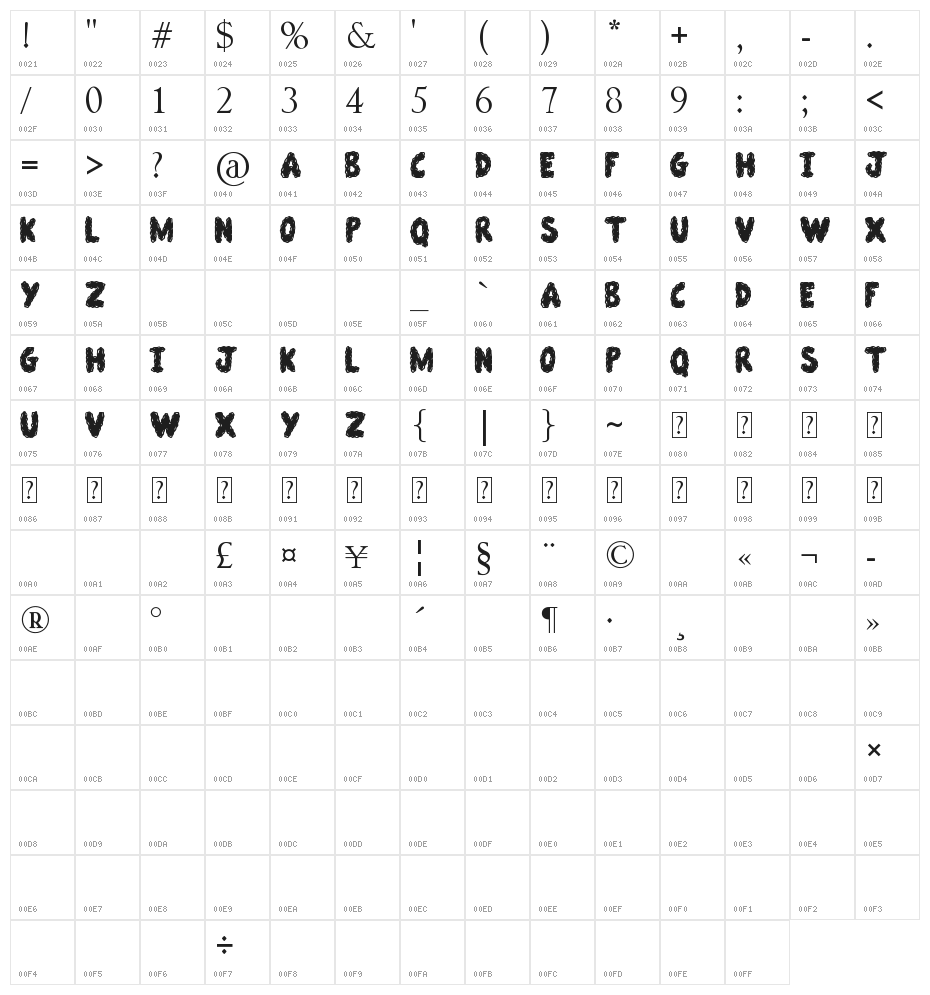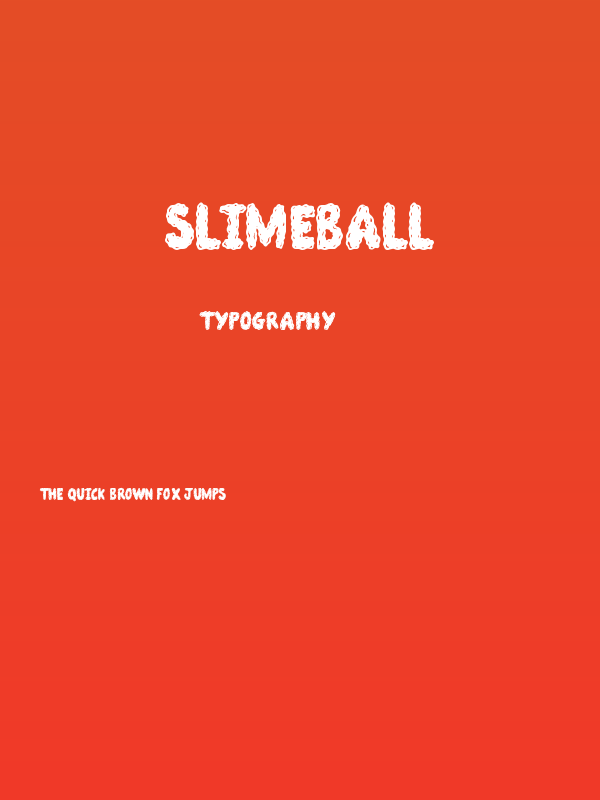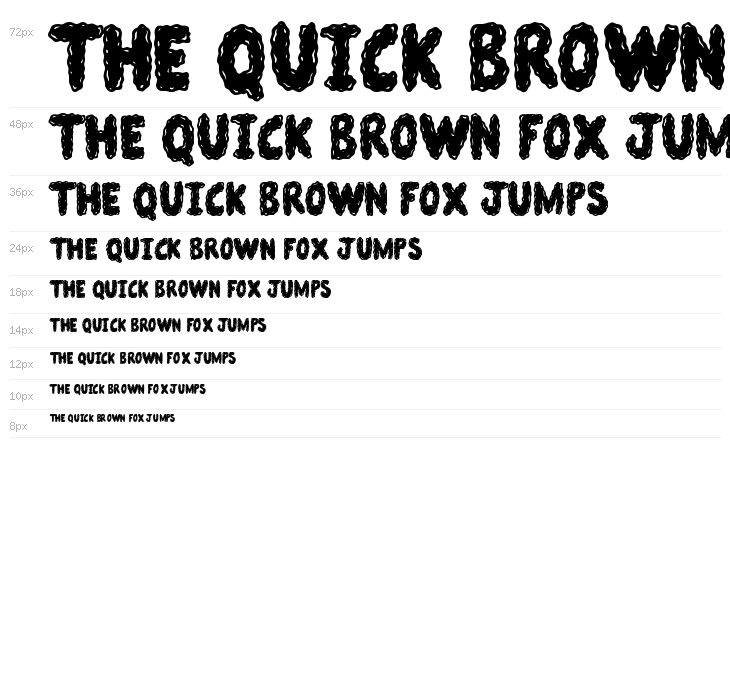
Slimeball Font
SLIMEBALL MAIUSCOLE
SLIMEBALL MINUSCOLO
SLIMEBALL ALTRI CARATTERI
| Stile generale | Playful, Organic |
| Progetti proposti | Ideal for children's book covers, playful branding, event posters, and creative social media graphics. |